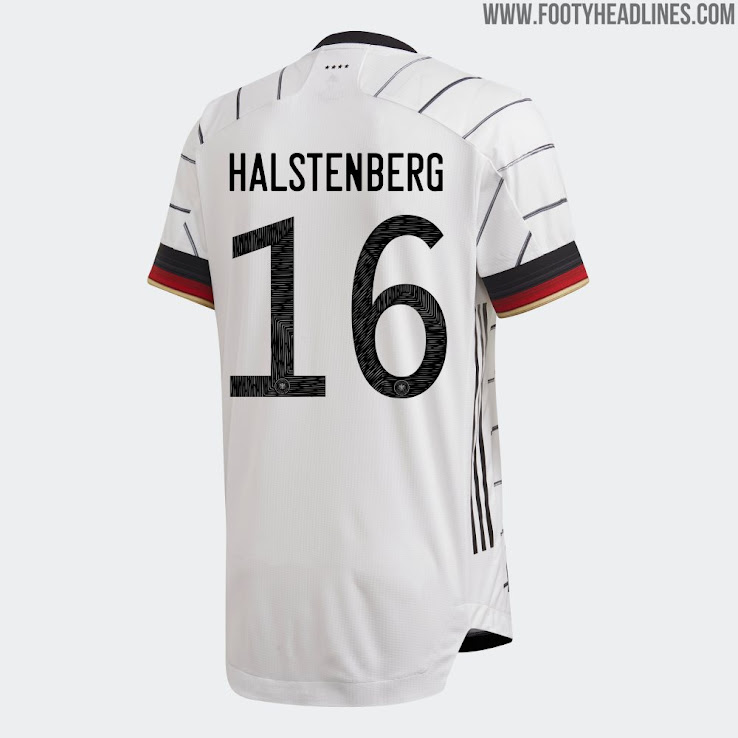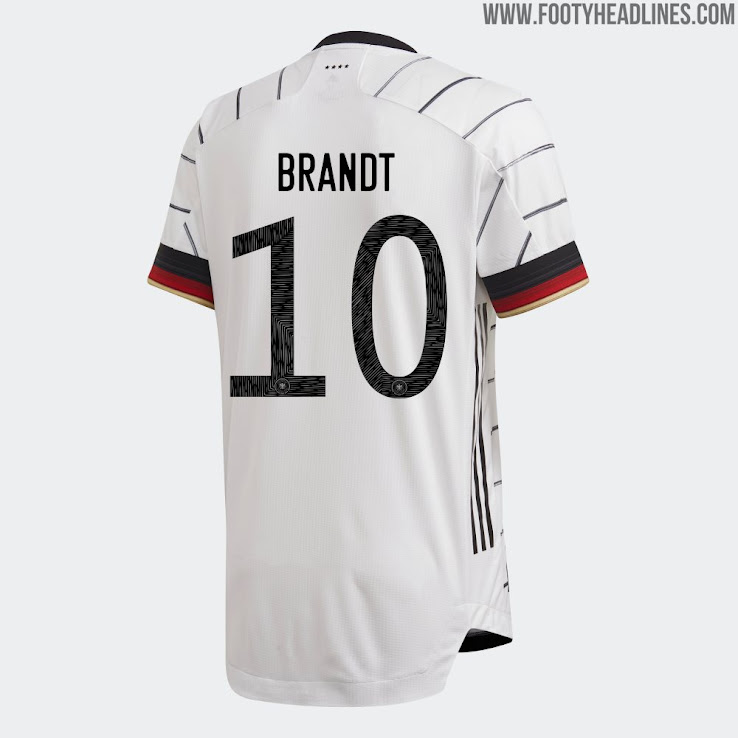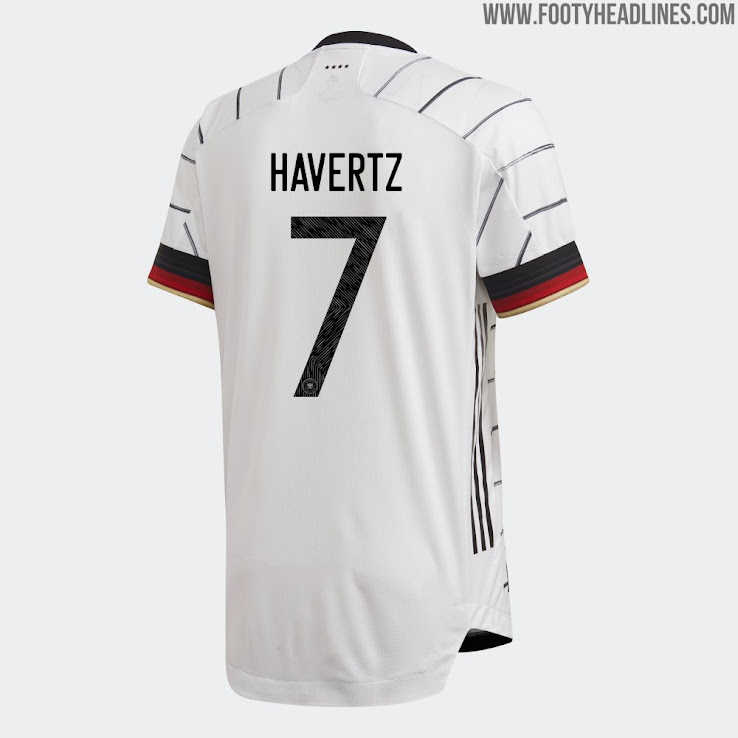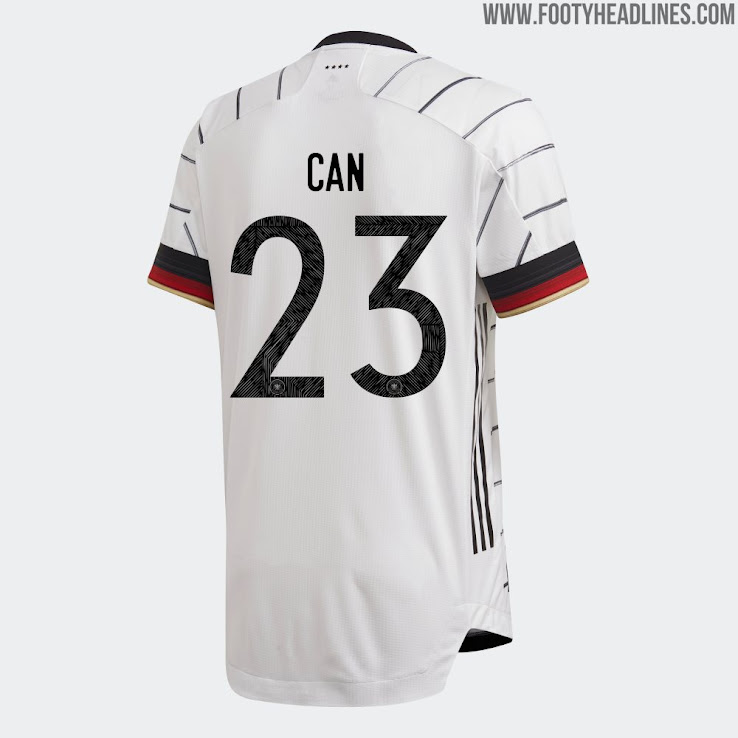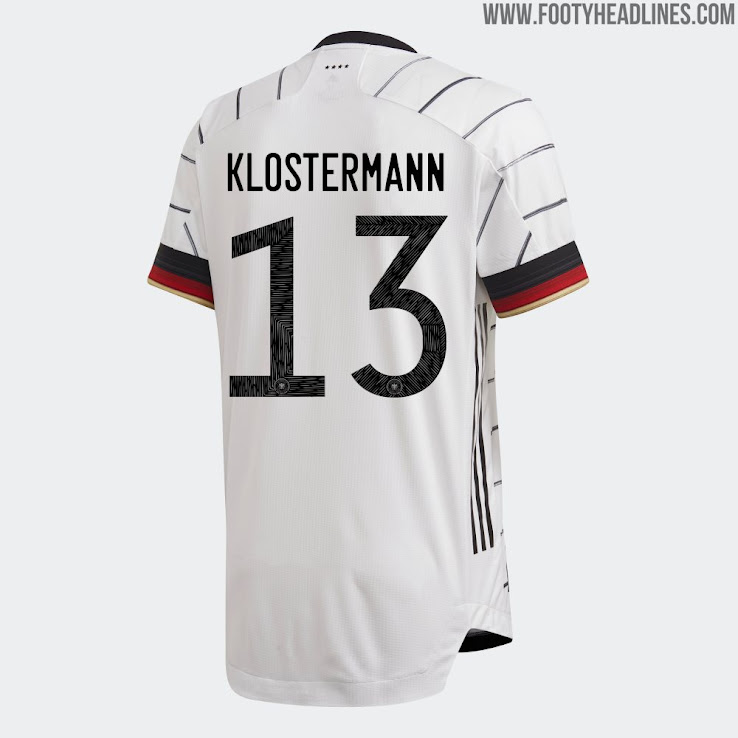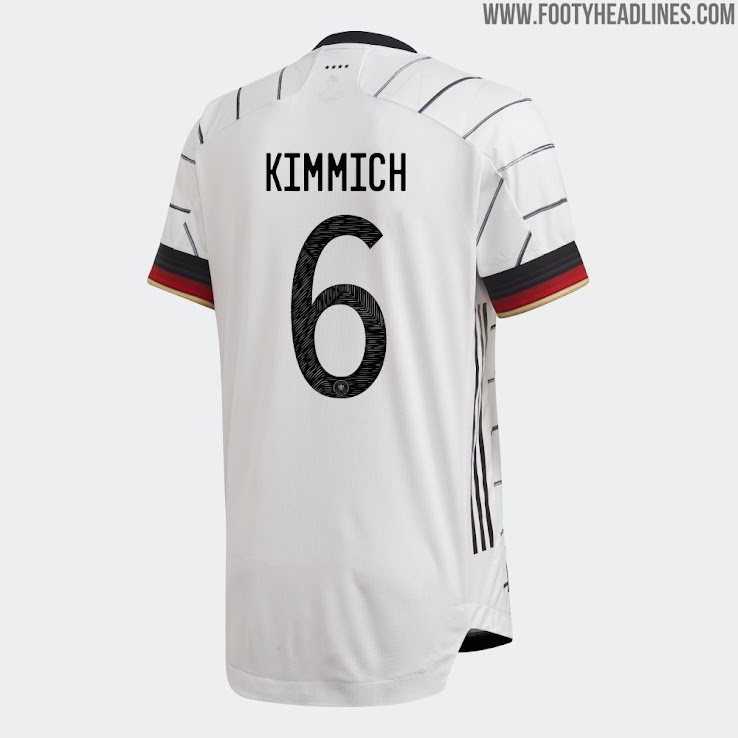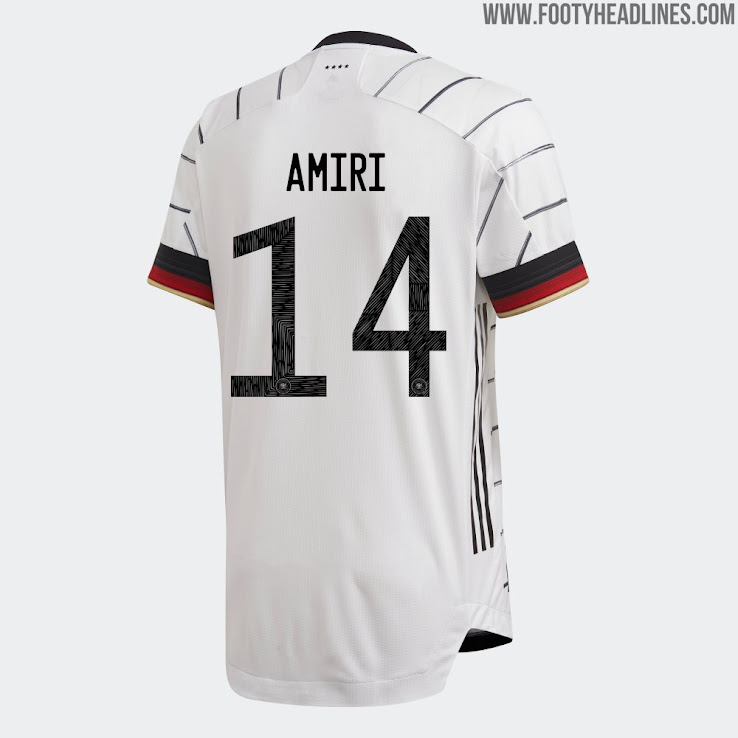
Adidas Deutschland EM 2020 Trikot-Schriftart Veröffentlicht - Doch nicht identische Schriftart für alle Teams?!
Anders als bisher erwartet, hat Adidas eine maßgeschneiderte Schriftart für das neue Deutschland EM 2020 Trikot entworfen. Werfen wir einen genaueren Blick auf die neue Deutschland EM 2020 Trikot-Schriftart.
Mit der neuen Deutschland EM 2020 Schriftart ist auch die Adidas WM 2018 Schriftart Geschichte. Die von allen Adidas-Teams bei der Weltmeisterschaft 2018 verwendete Schriftart mit kyrillischen Buchstaben und Zahlen sorgte für eine große Verwirrung bei den Zuschauern.
Adidas Deutschland EM 2020 Trikot-Schriftart - Exklusiv für Deutschland entworfen
Die neue Adidas Deutschland 2020 Trikot-Schriftart ist auf perfekte Lesbarkeit ausgelegt - so steht die Schriftart im starken Kontrast zu der von 2018, wo jeder Buchstabe und jede Zahl "aussieht, wie sie aussehen soll". Der Stil selbst erinnert uns an eine normale Windows-Schriftart.
Innerhalb jeder Zahl befindet sich ein subtiles Grafikmuster aus Linien. Das DFB-Wappen befindet sich am unteren Ende der Nummern.
Wir gehen davon aus, dass die Deutschland 2020 Schriftart auch auf dem Auswärtstrikot zu finden sein wird.